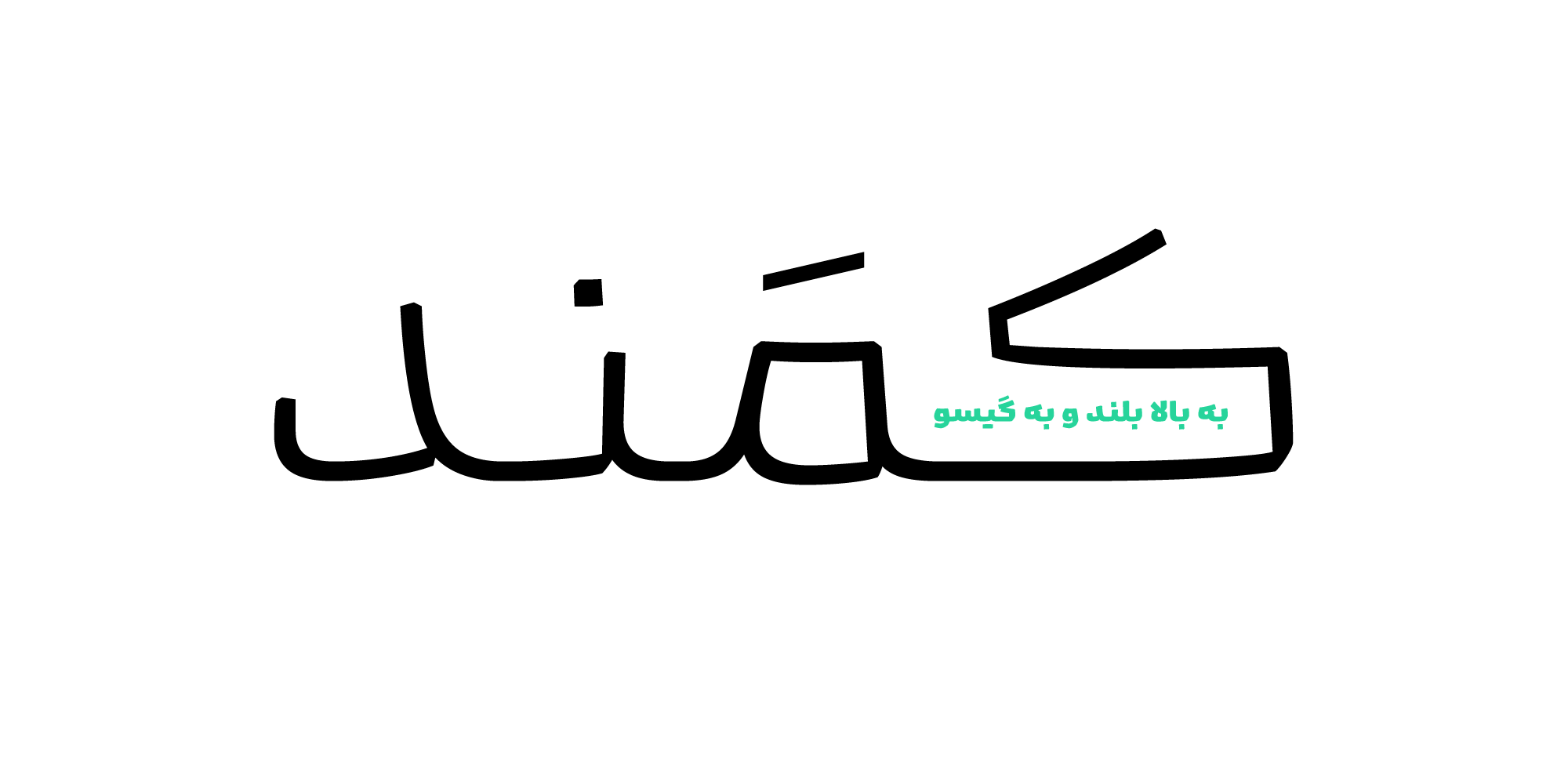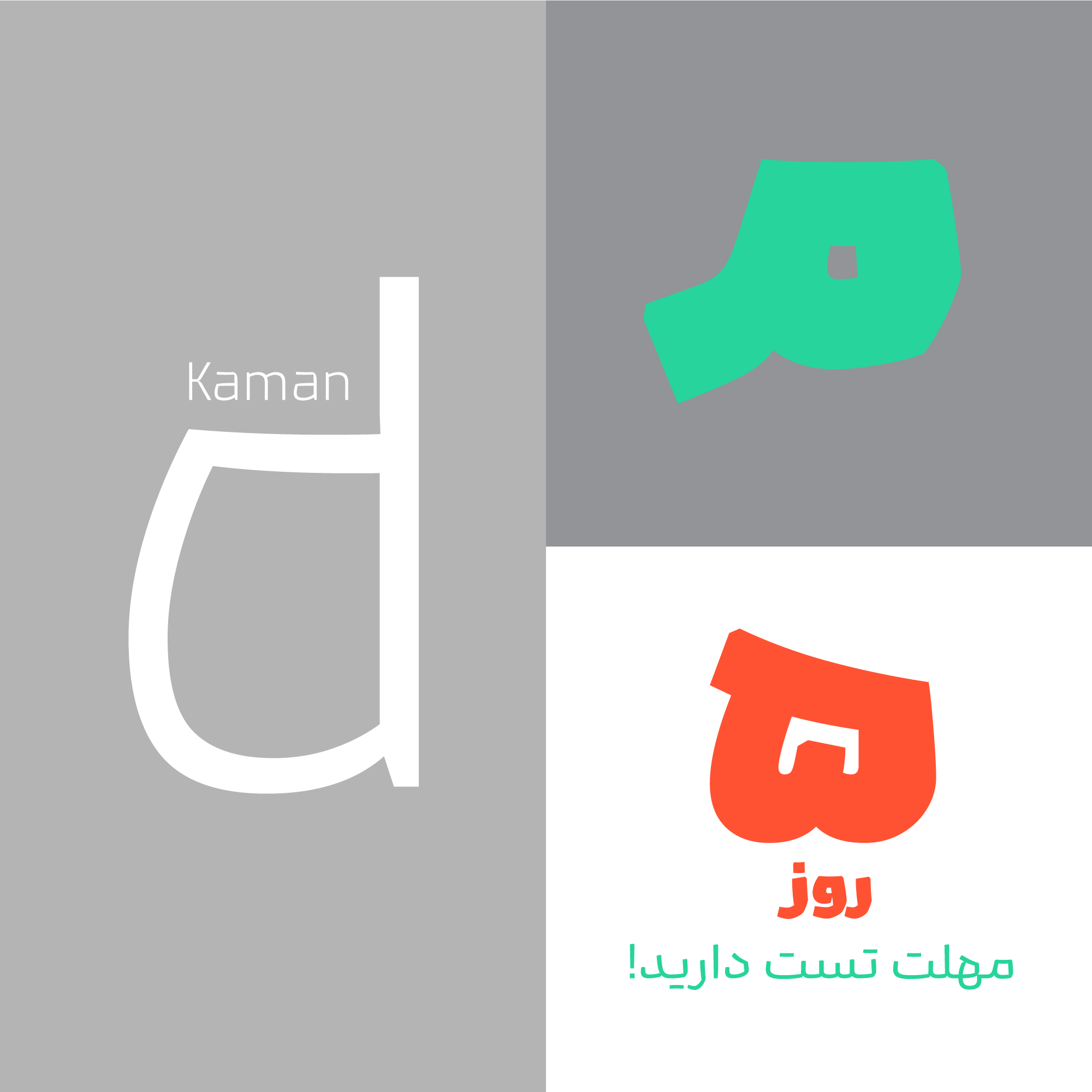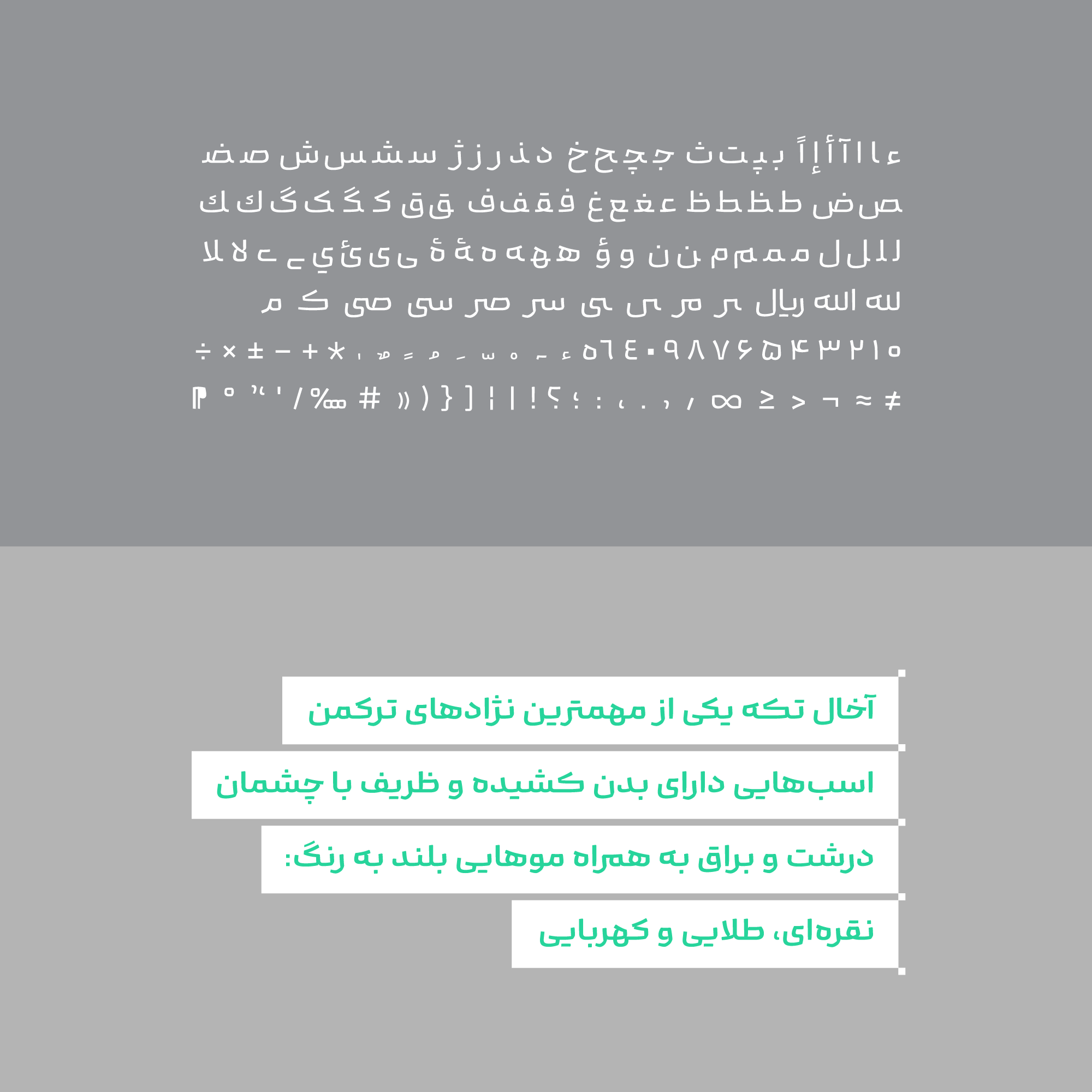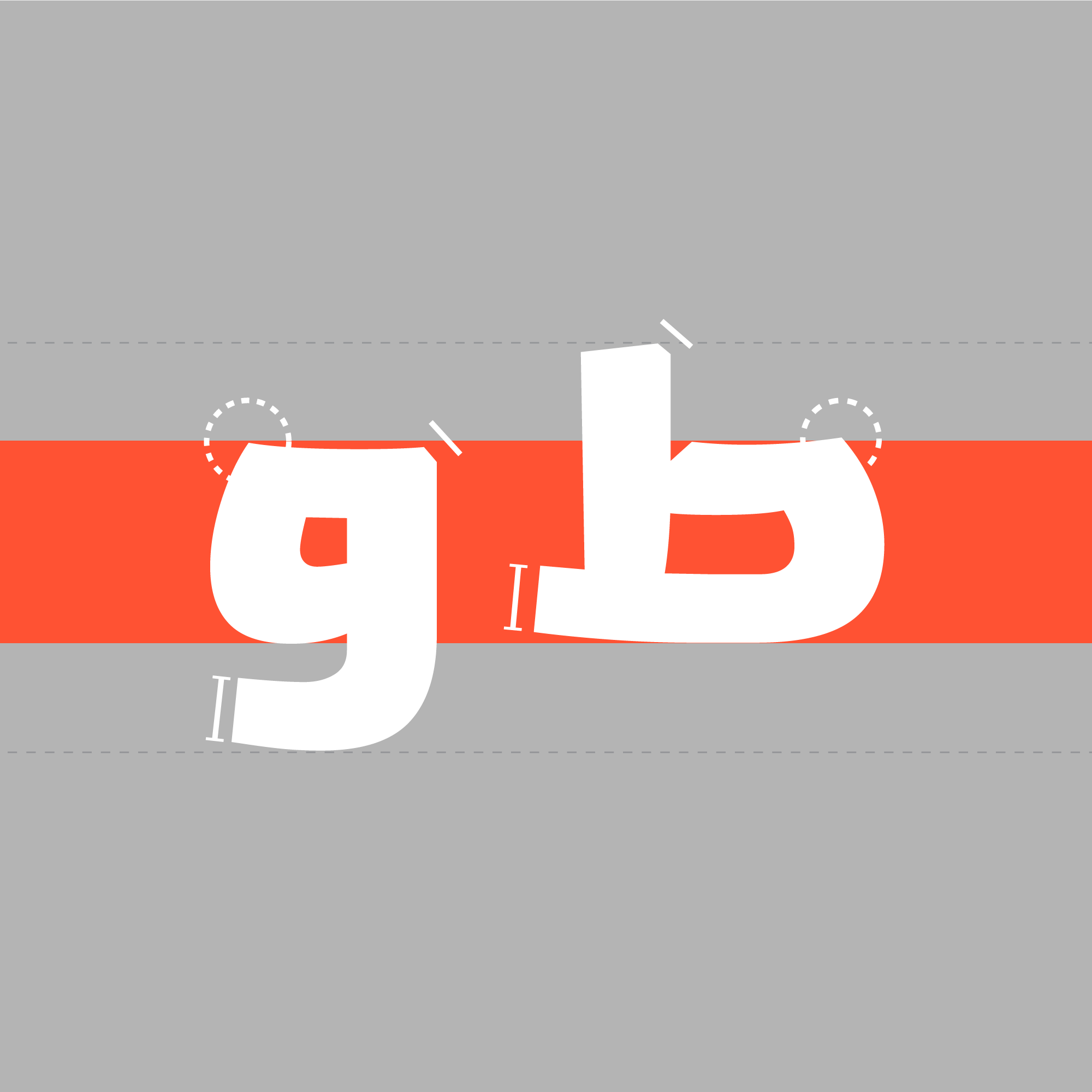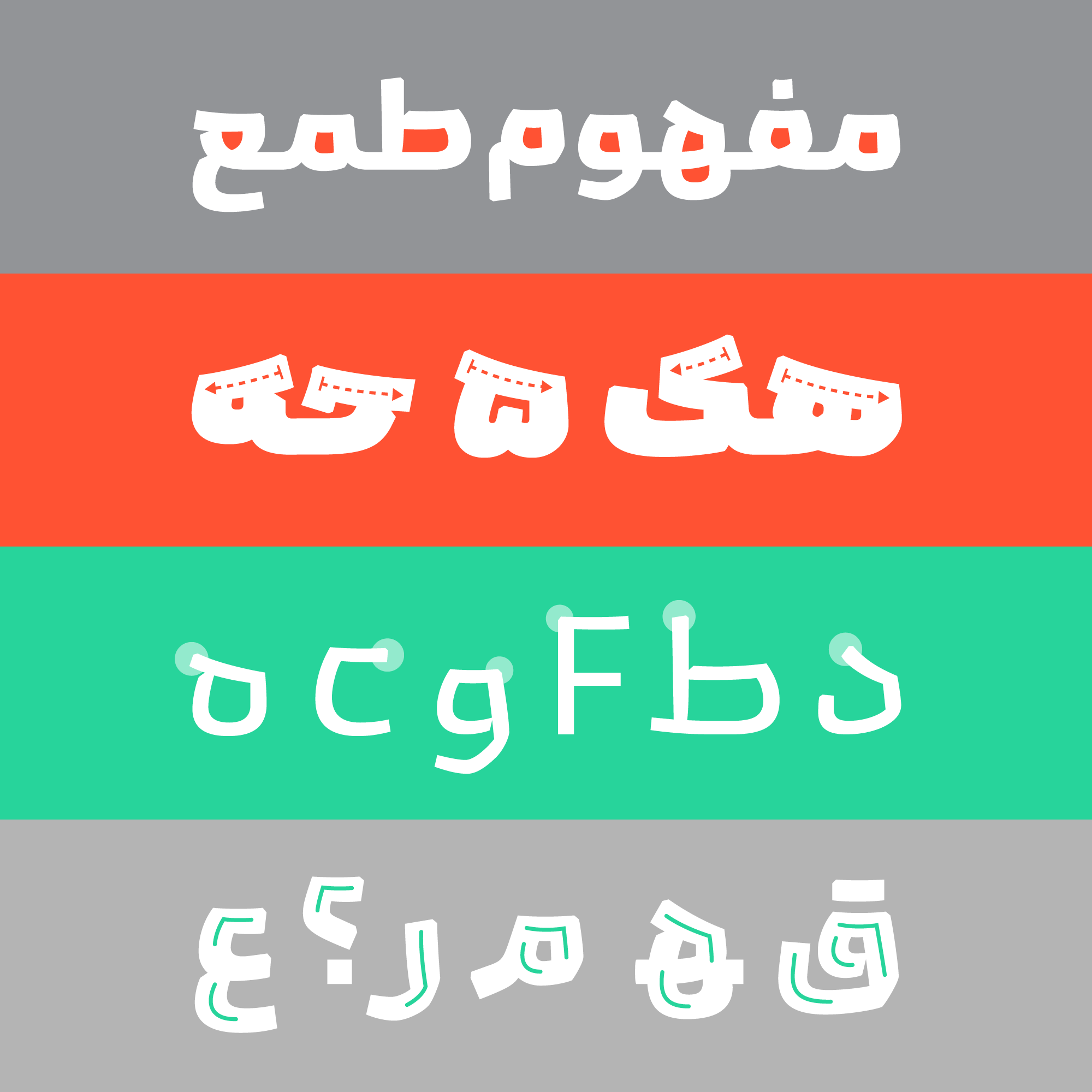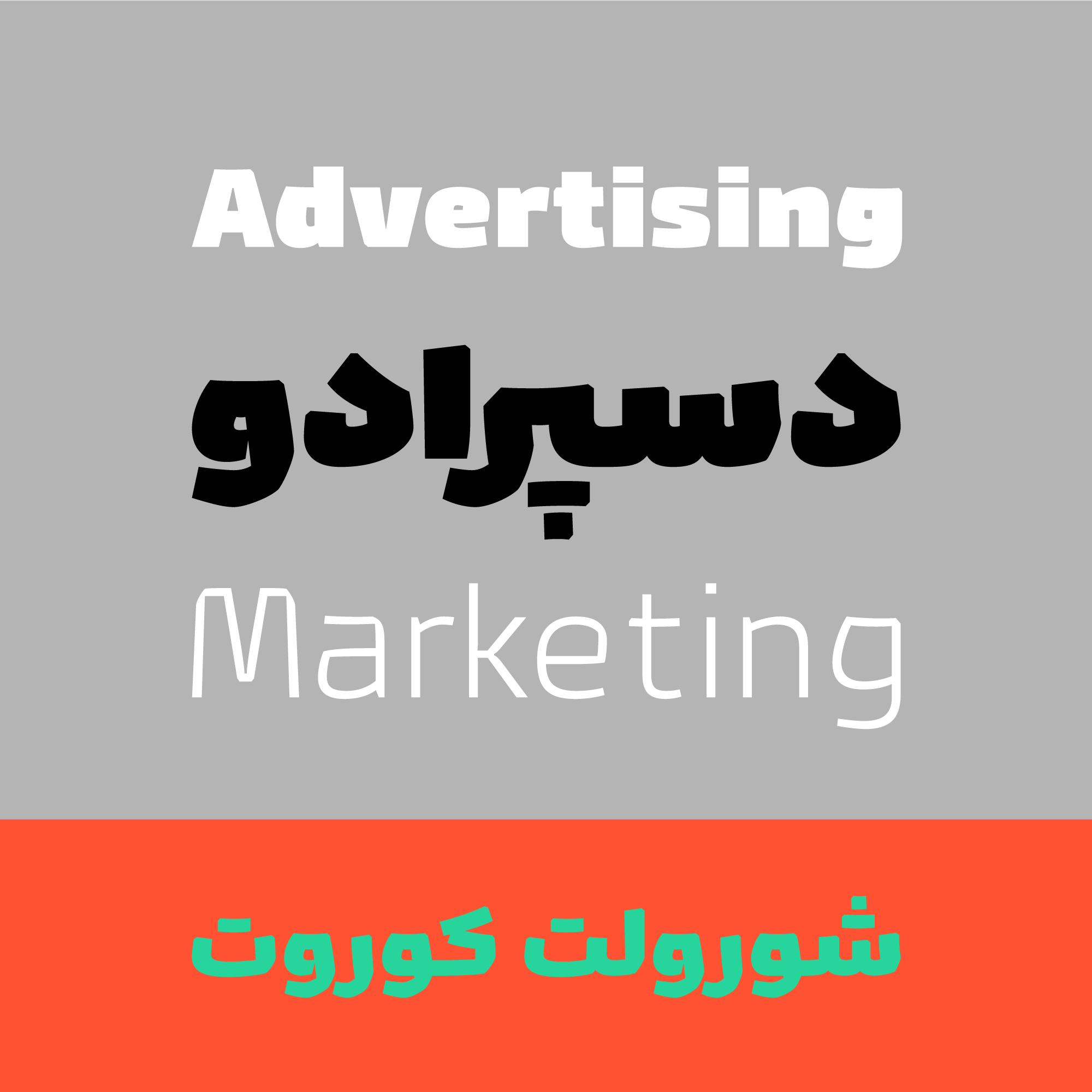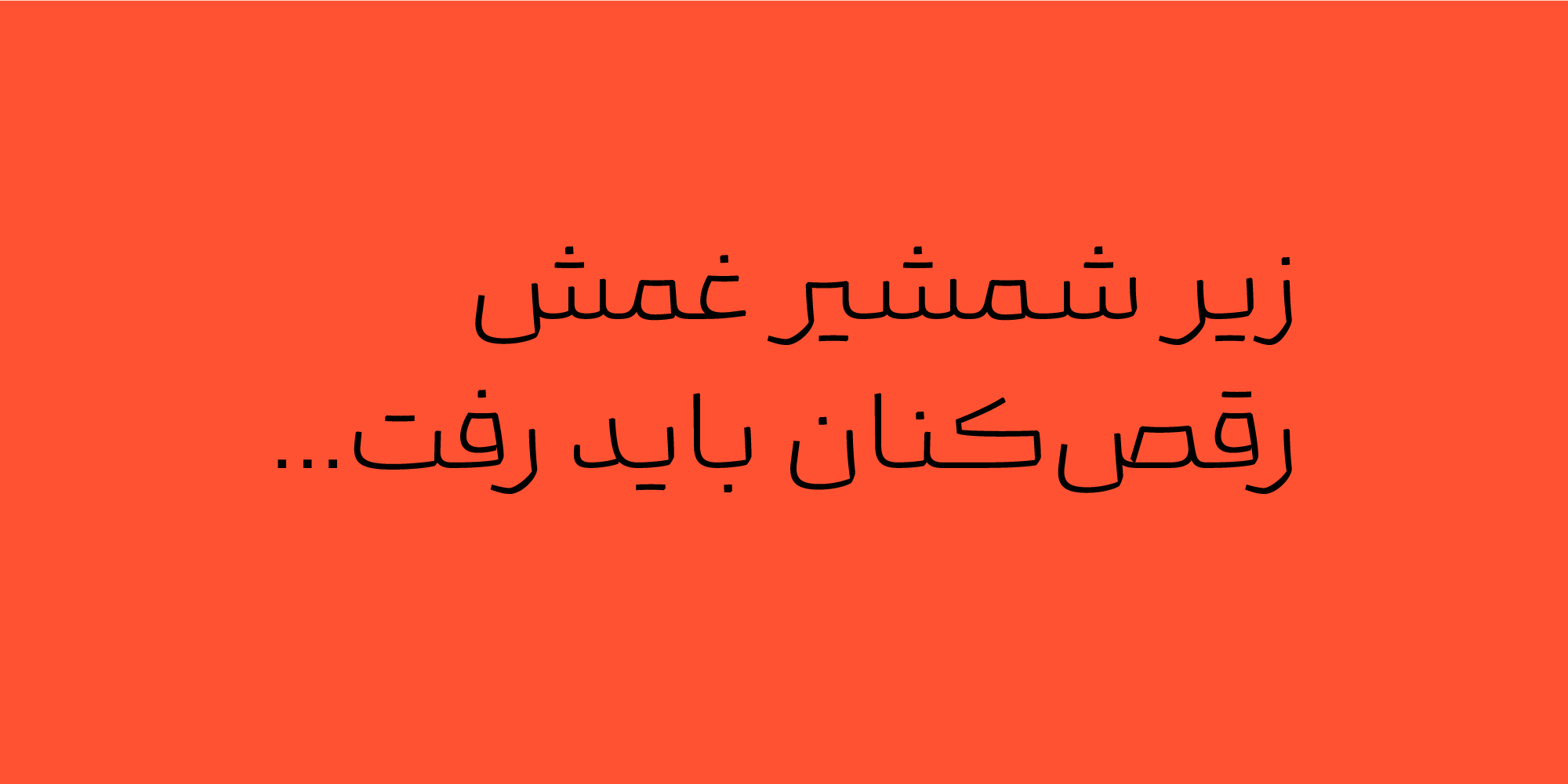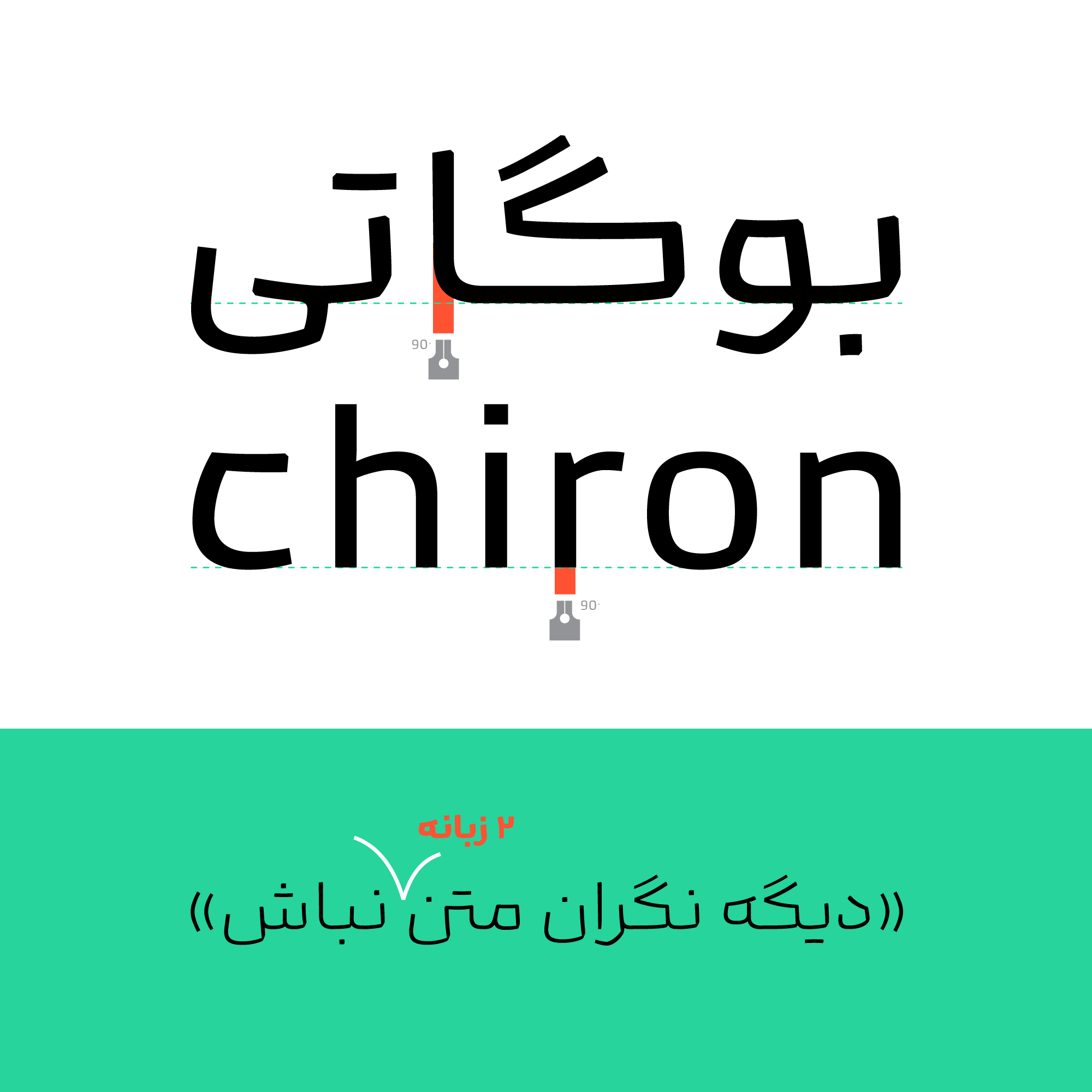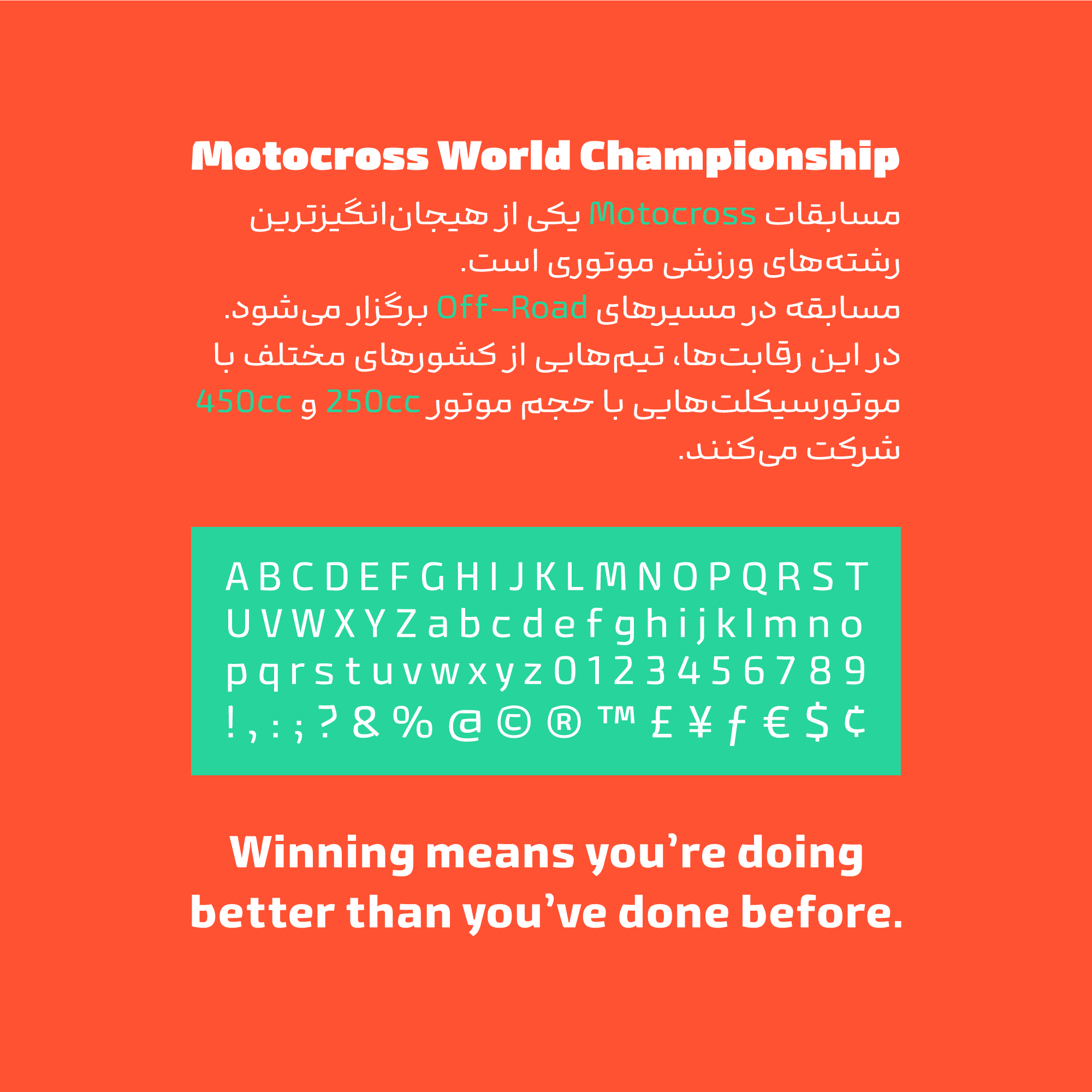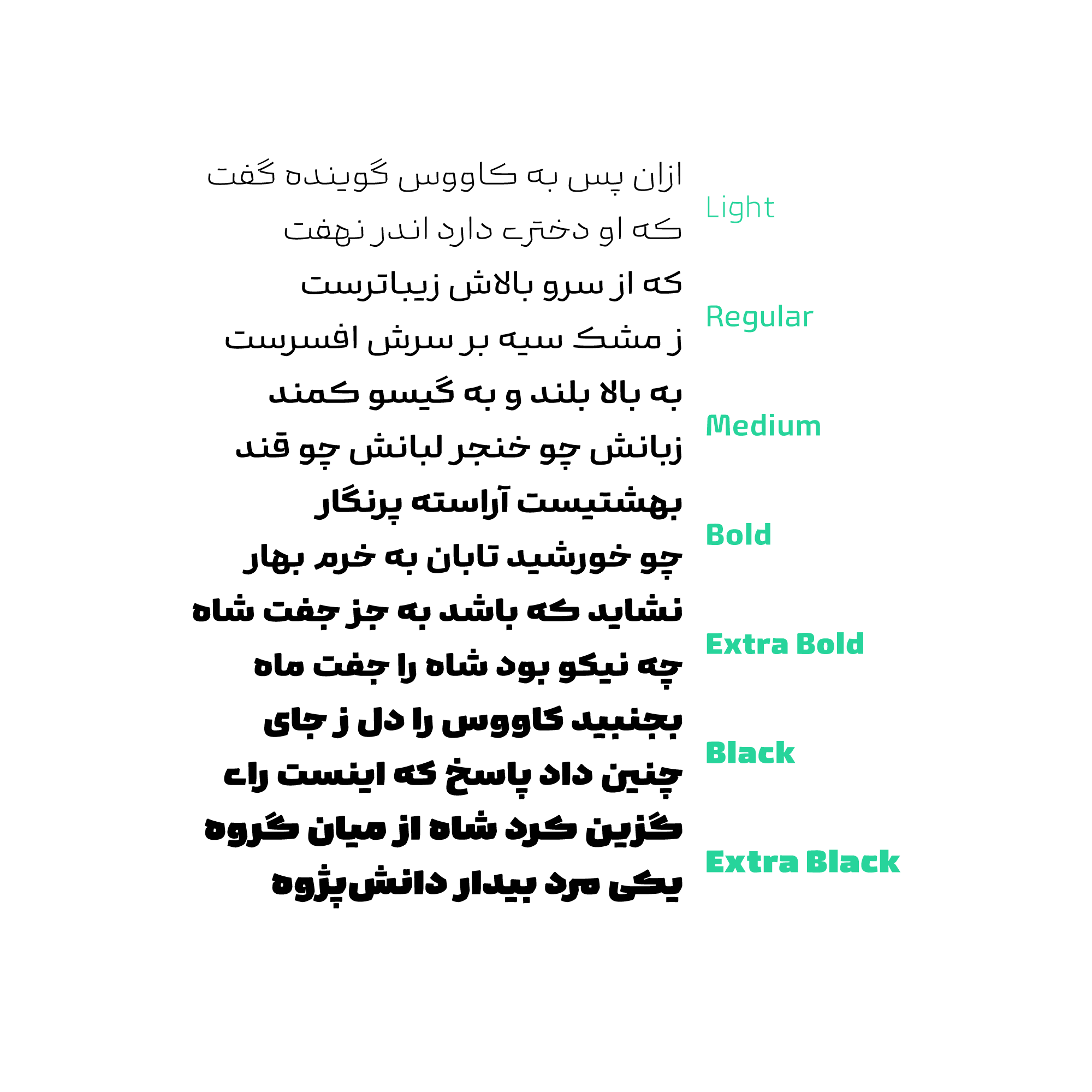
اسب سرکشی را تصور کنید که خرامان خرامان در دشتهای سبز و زیبا حرکت میکند و یالهای زیبایش در میان بادها به هر سویی پریشان میشود.
کمند همان اسب چموش و دلفریب است که با هر شلاقی رام نشده و سوارش را غافلگیر میکند.
فونت کمند رفتار فرمی اصیل و مبتنی بر خط نسخ دارد اما در جزئیات غیر قابل انتظار و پرهیجان است؛ این هیجان و جذابیت فرمی کاملا آگاهانه انتخاب شده و جزء جدا نشدنی تبلیغات امروز است.
از ویژگیهای فرمی کمند میتوان به موارد زیر اشاره کرد:
فرمها در هر کاراکتر و هر حرکتی از جایی که انتظارش را نداریم یا برش میخورد یا میشکند و یا خلاف جهت میچرخد.
ارتفاع صعود و نزولها کوتاه است و گویی در بدنه حروف حل شدهاند. این مدل طراحی کمک میکند تا جذابیت تایپفیس در تبلیغات محیطی و فضای مجازی بالاتر برود.
وجود وزنهای مختلف و همچنین امکاناتی مانند لیگچرها (حروف ترکیبی) و آلترناتیوها (حروف جایگزین) از جمله جذابیتهای دیگر کمند است.
برای کمند فونت انگلیسی هم طراحی کردیم این کار باعث میشود در متنهای دوزبانه هماهنگی بهتر و روانتری بین دو زبان برقرار بوده و یکپارچگی متن کامل حفظ شود.
تلاش ما این بود تا فرمهایی بدیع و تازهای را به جریان تایپدیزاین امروز ایران اضافه کرده و تا جای ممکن کلمات در نهایت زیبایی و چشمنوازی در کنار هم نشسته و ترکیبی منسجم را بسازند.
این تایپفیس در بهار و تابستان ۱۴۰۳ توسط امید امامیان و مهدی ارشادی در ۷ وزن طراحی و منتشر شد.
لازم به ذکر است گسترش آن برای زبانها و سبکهای دیگر ادامه دارد.